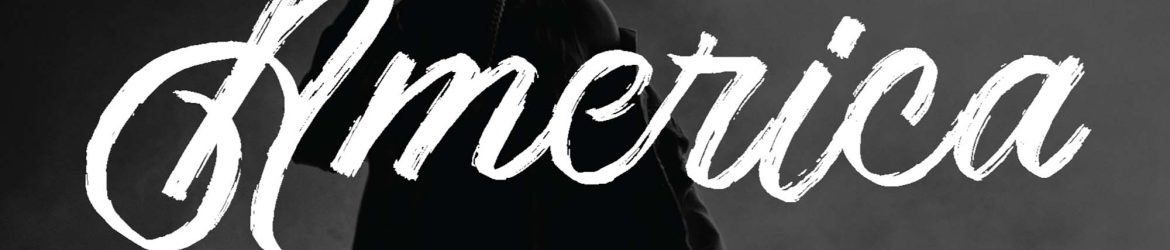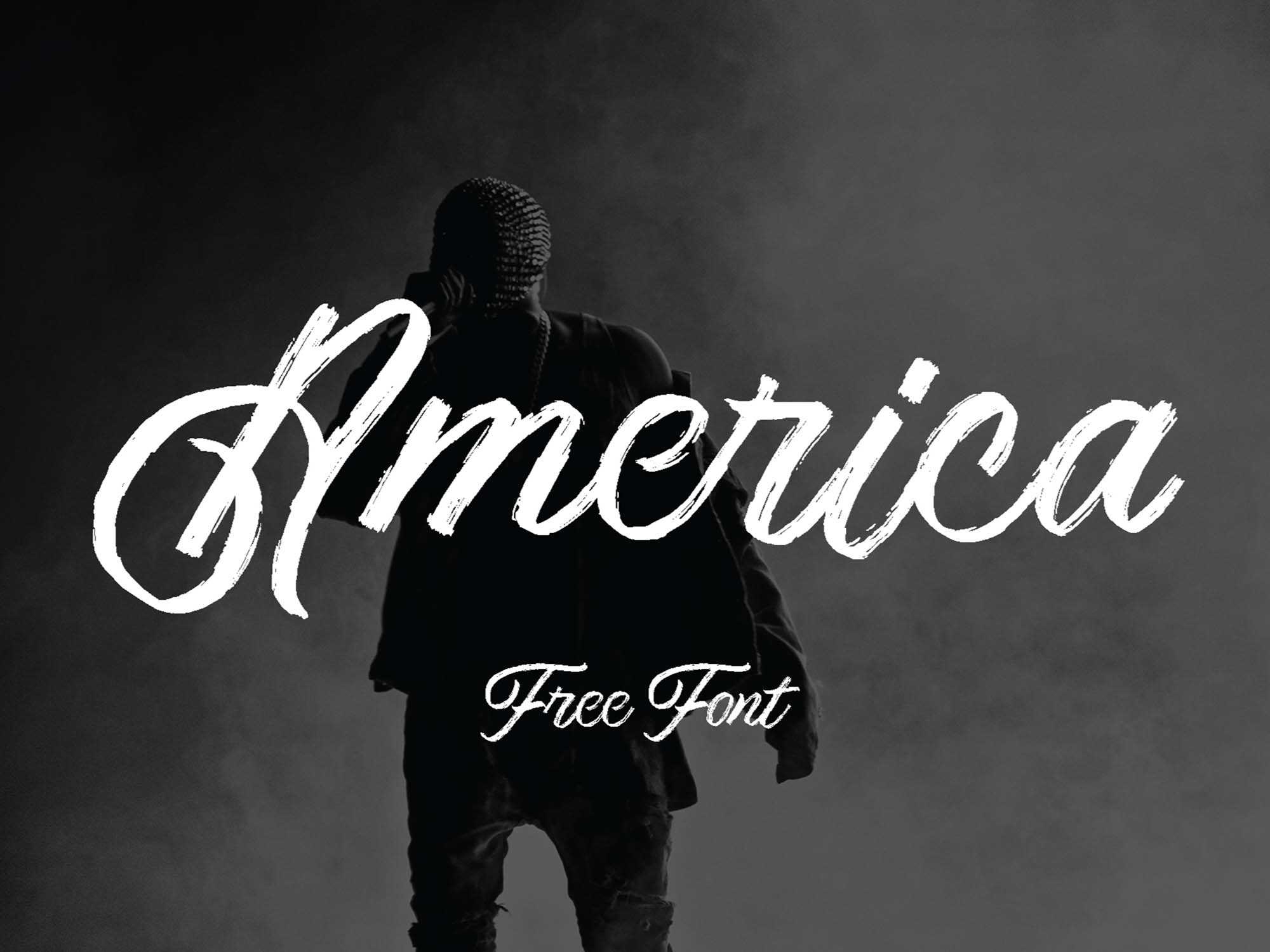
America Script Font
Se você está procurando por uma fonte de script perfeita que atenda a todas as suas expectativas para um design, você não está sozinho. A popularidade da mídia digital significa que destacar-se no meio de tantos trabalhos de design é algo que exige um esforço maior. Por isso, nunca deve ver fontes como um pequeno componente no todo do design UI, mas como um elemento essencial que pode levar seus designs a um novo patamar. O America Script Font é uma fonte de script que você pode adicionar aos seus projetos, e que certamente o ajudará a destacar-se no meio de uma multidão. Com sua delicadeza e sofisticação, essa fonte trará um toque único a qualquer projeto que você criar. Instale-o e faça a diferença em suas criações.